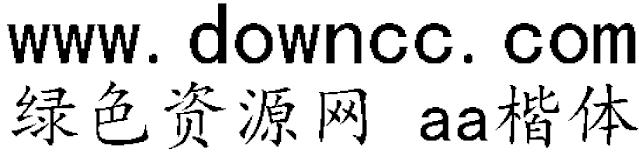
aa楷体字体包能够让你在oppo手机上直接使用aa楷体字体进行系统字体设置以及各类字体输入与运用,让你在使用的时候感受到规整的楷体字体体验,快来绿色资源网下载吧!
aa楷体完整版ttf字体介绍
楷书也叫正楷、真书、正书。从程邈创立的隶书逐渐演变而来,更趋简化,字体的大小可以在手机设置中调节,更多字体可在绿色资源网检索下载!
字体的形式十分多样,拥有手机字体电脑字体,能够在不同场合实现不同的显示效果
通过对字体的最正确运用,将让你拥有赏心悦目的体验